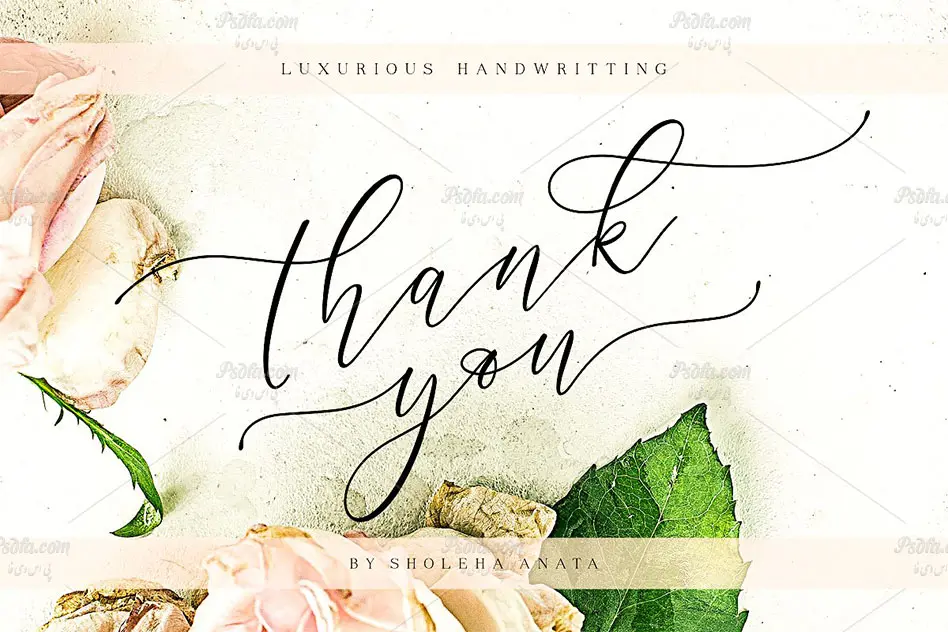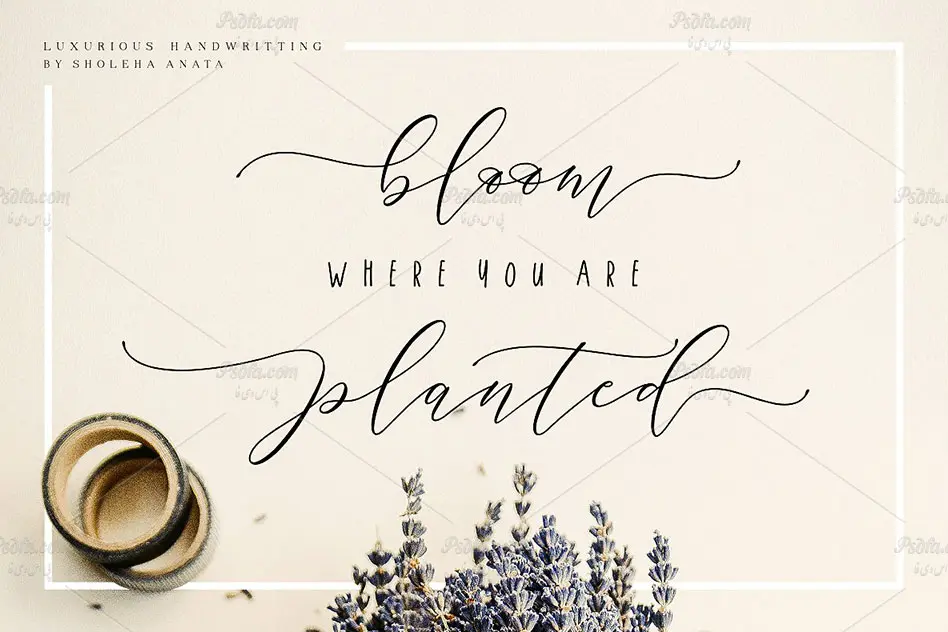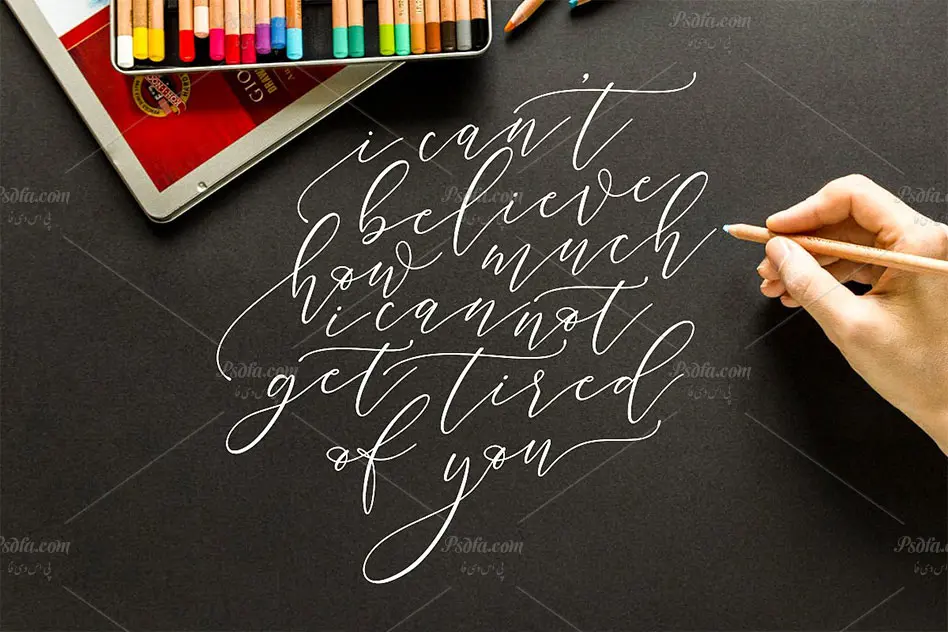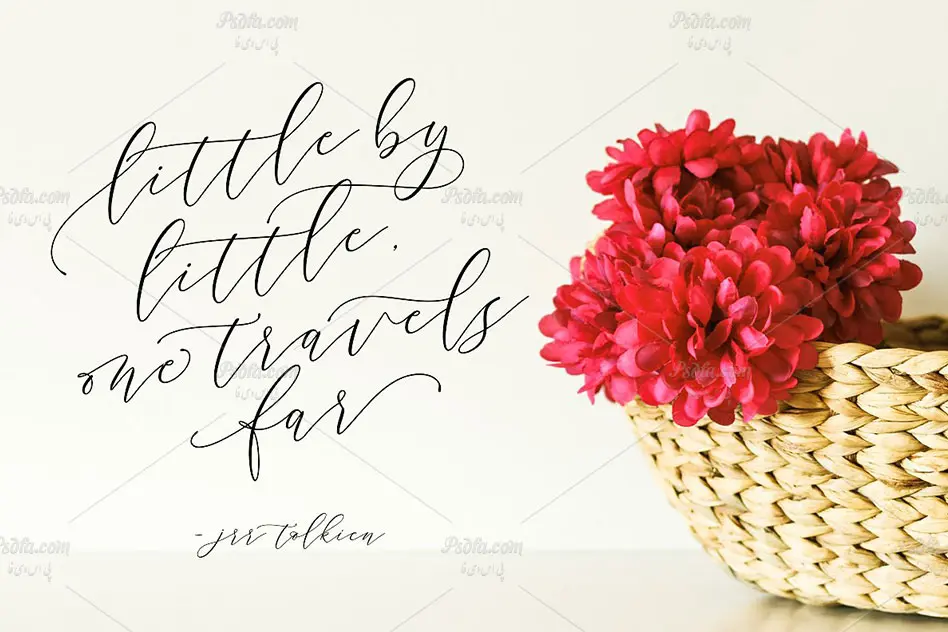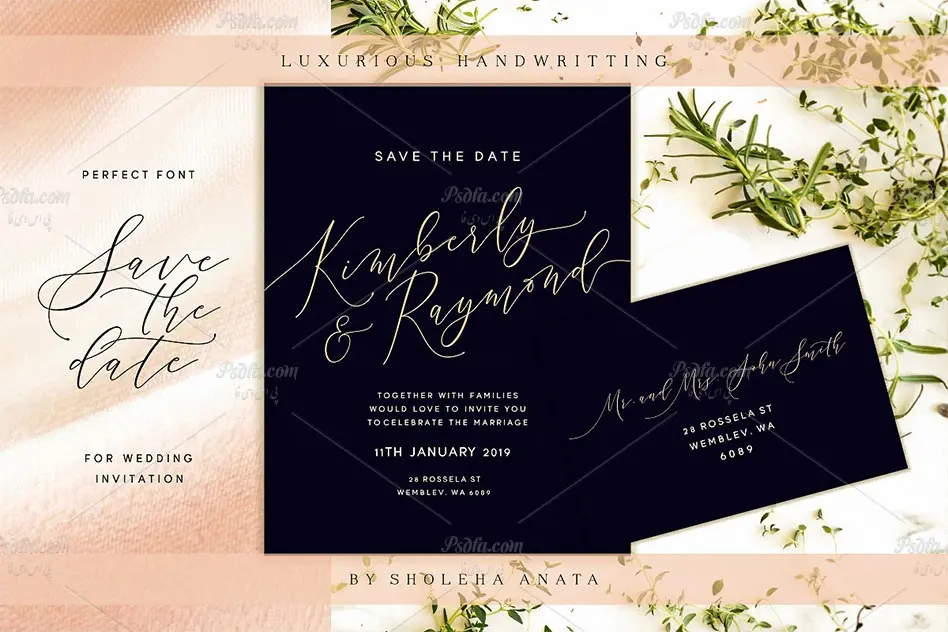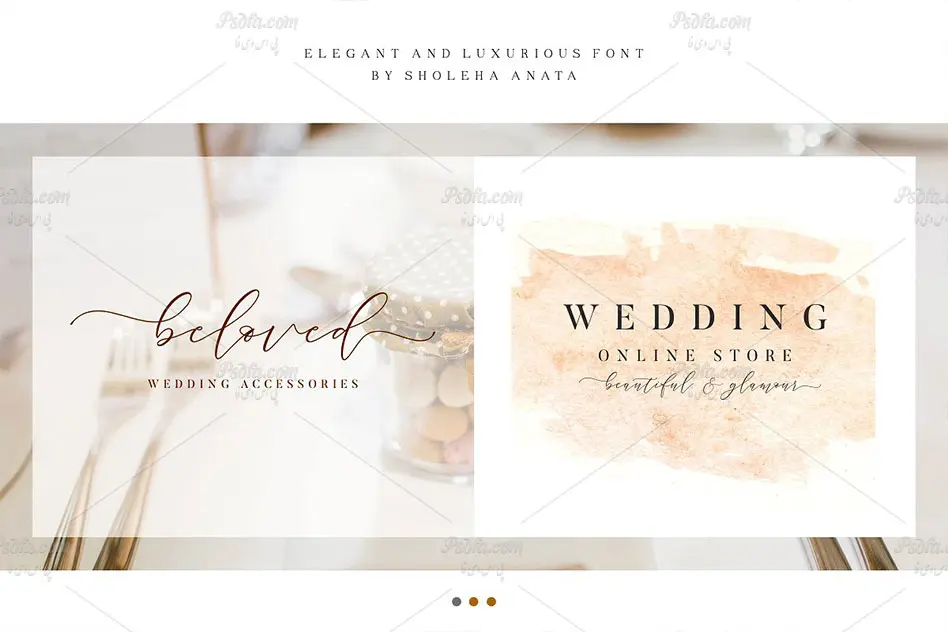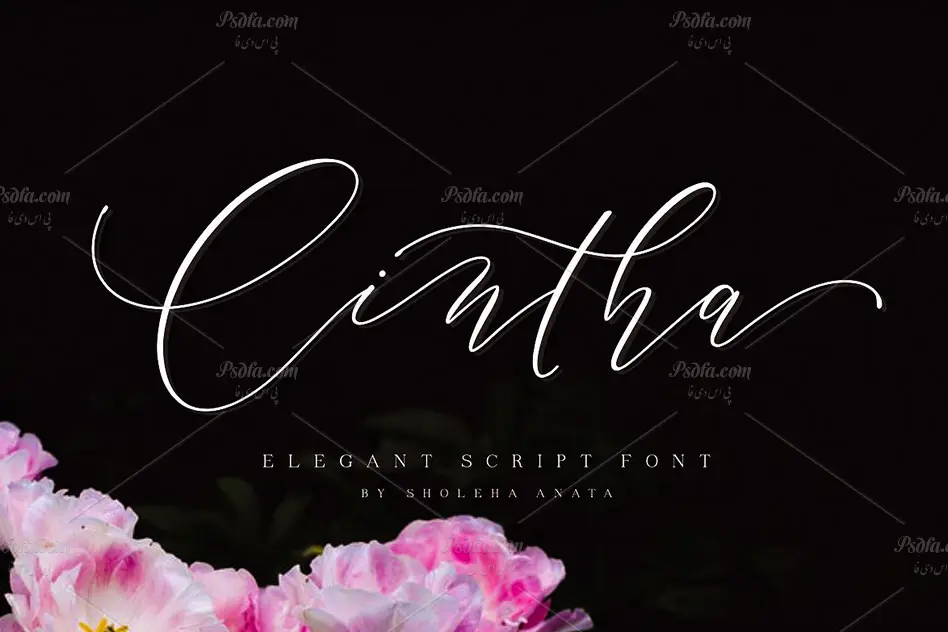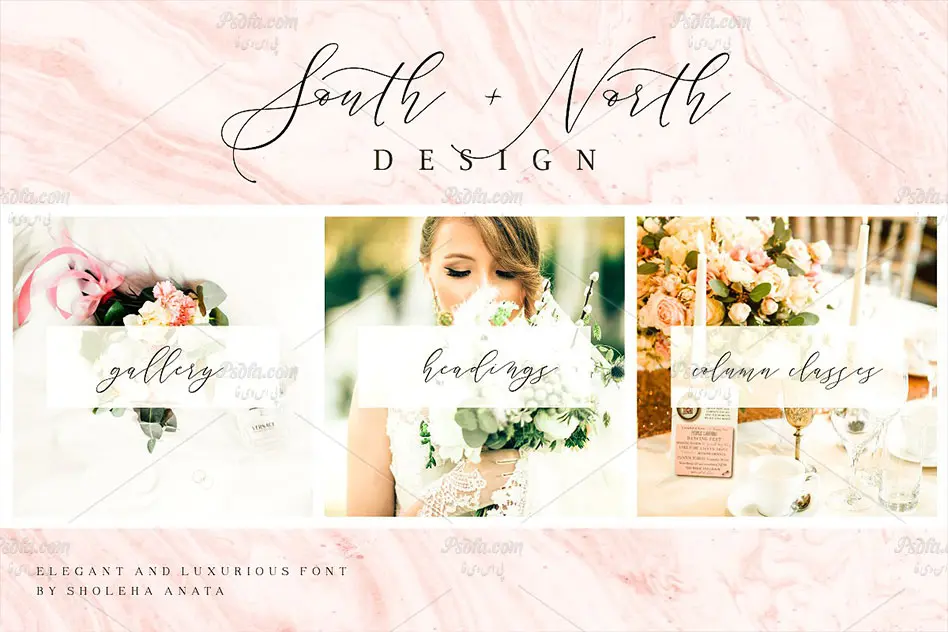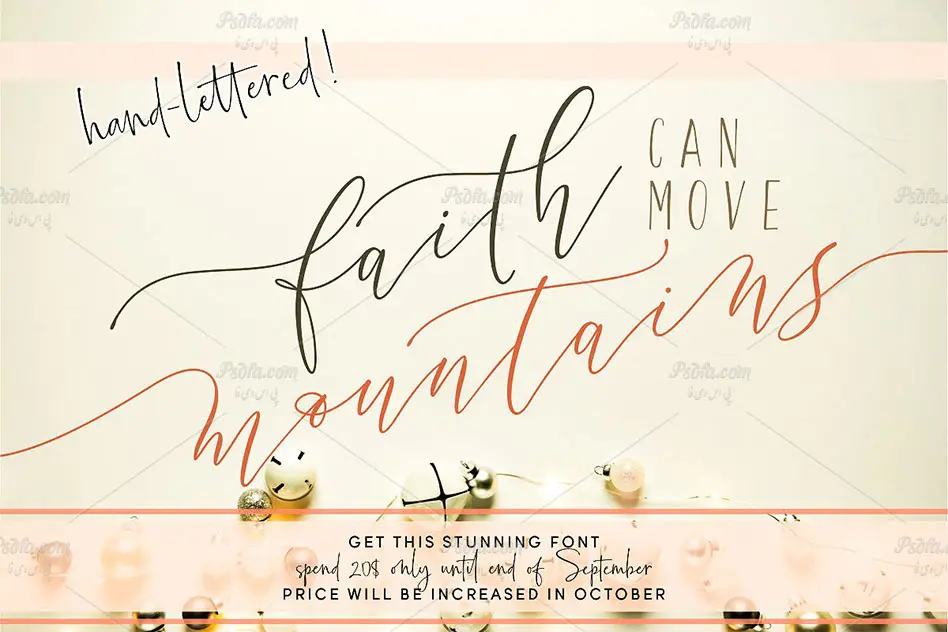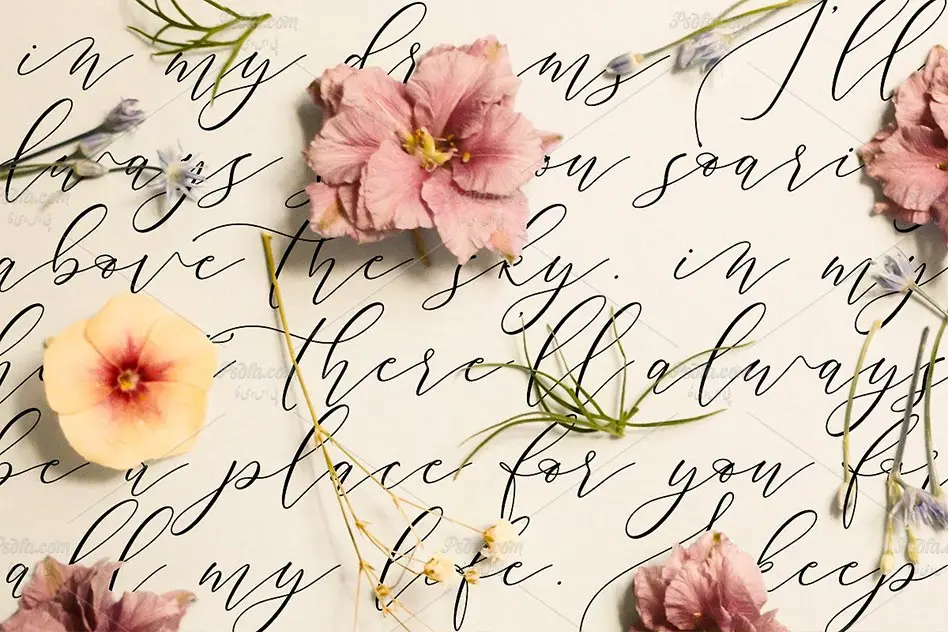
در این پست شاهد فونت انگلیسی و دستنویس Cintha مناسب جهت استفاده در طرح های گرافیکی می باشید. این فونت فوق العاده زیبا در قالب 4 فایل otf و ttf در سایت بارگذاری شده است که پس از نصب یکی از این دو فرمت در پوشه فونت های سیستم قادر به استفاده از آن ها در تمام نرم افزارهای گرافیکی و ویرایشگر متن از جمله نرم افزار فتوشاپ ، مجموعه نرم افزار آفیس ، ایلاستریتور ، افترافکت و … خواهید بود. فونت Cintha در چهار طرح متفاوت و زیبا ایجاد شده است که بسته به نیاز و سلیقه خود می توانید از هر کدام استفاده کنید. از این فونت زیبا می توان در طراحی انواع کارت عروسی ، کارت پستال ، کارت تبریک ، طراحی انواع پوستر ، کارت ویزیت و … استفاده نمود.